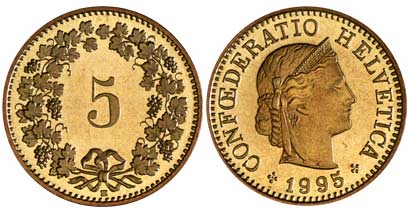
Polizeischutz für die Fraktur.
Mit Pfennigmünzen hätten die das ganze Projekt glatt zum halben Materialpreis durchziehen können. Da hat wieder keiner drüber nachgedacht bei der Währungsumstellung, was das für die Schönen Künste bedeutet. :neenee:
Soweit ich weiß werden die "Altgeldbestände" von der Bundesbank vernichtet bzw. recycelt.
Und man kann ja auch nicht mal eben 250000 Münzen aus privatem Restbesitz aufttreiben :wink:
Ich meinte ja, daß dies dann billiger gewesen wäre, wenn man mit Rücksicht auf solche Kunstprojekte auf die Währungsreform verzichtet hätte. Dann wäre der (logistische) Beschaffungsaufwand für Pfennige nicht höher als der für die Cent-Münzen gewesen.
Tröstet Euch: Bei uns ist die kleinste Münze der Fünfräppler. Wären dann gut 3 Euro-Cent. Die Installation wär hier nochmal eine gute Ecke teurer gekommen.
Dabei fällt mir grad auf, dass das «Helvetica» extrem schlecht zugerichtet ist, oder? Einfach um wieder mal über… Typographie zu reden. 8)
Bei uns ist die kleinste Münze der Fünfräppler.
Wie jetzt? Werden da alle Beträge gerundet?
(Einfach um wieder mal über Geld zu reden …)
Warum denn nicht? In Finnland gibt es ja auch keine Ein- und Zwei-Cent-Stücke.
Bei uns ist die kleinste Münze der Fünfräppler.
Wie jetzt? Werden da alle Beträge gerundet?
Jupp.
Bis zum 1. Januar 2007 gab es zwar offiziellerweise noch ein Einrappenstück – das war aber schon lange nicht mehr im allgemeinen Gebrauch, ich hab jedenfalls in meinem Leben noch nie eins gehabt oder gebraucht (noch einen Preis im Supermarkt o.ä. gesehen, der nicht auf 5 Rappen gerundet gewesen wäre).
Das Problem ist, dass sowohl Ein- als auch Fünfräppler in der Herstellung teurer sind als ihr Nominalwert. Daher sollte vor zwei Jahren auch der Fünfräppler abgeschafft werden – das hätte immerhin jährliche Ausgaben von 300 000 Franken eingespart, schreibt die NZZ –, den haben sie uns dann aber trotzdem gelassen, wegen des kulturellen Wertes. (Wir und unser Geld ... Da wurde von manchen Politikern mit der «hohen emotionalen Bindung» an den Fünfräppler argumentiert. Auch NZZ, Link oben.)
Warum denn nicht?
Wenn ich z. B. einem Kunden 89 € in Rechnung stelle, sind das durch die Mehrwertsteuerbelastung von 19% dann EUR 105,91. Wie soll ich das denn buchen, wenn es nur runde Beträge gibt? Das stimmt die Kasse doch nie. Wenn wir keine Centmünzen hätten, wäre zu befürchten, daß künftige MwSt.-Erhöhungen gleich in Schritten zu 5 Prozentpunkten stattfänden un krumme Endbeträge zu vermeiden. Das wäre gar nicht lustig.
Daß ausgerechnet die Schweizer mit ihrem Buchhalter-Ruf sich aufs runden verlegen, ist doch sehr erstaunlich.
Wir stellen unseren Kunden einfach keine so kläglichen Rechnungen. Unsere Honorare sind nämlich deshalb astronomisch, dass wir die MWST. immer großzügig abrunden können.